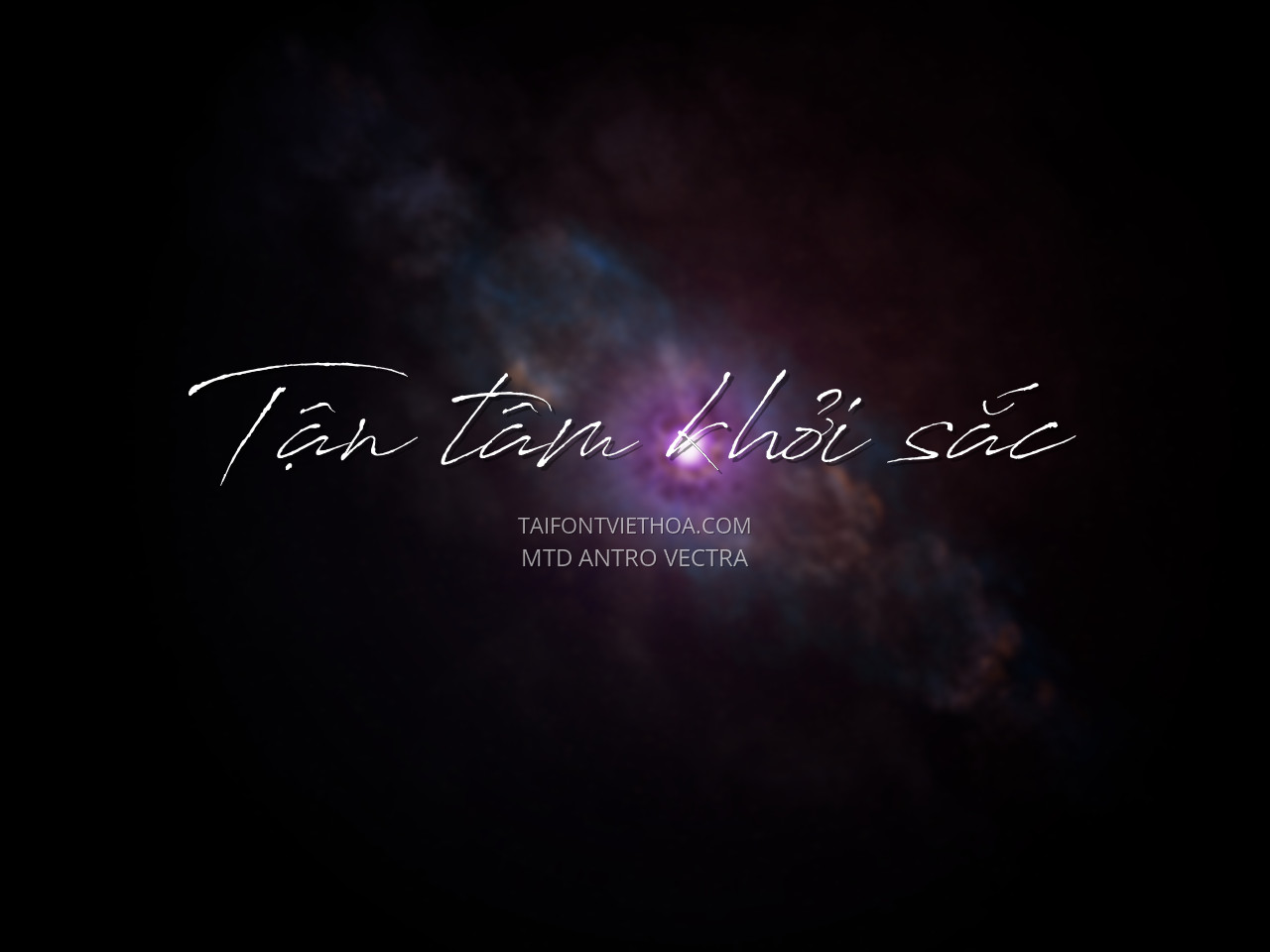
Giới thiệu về font Antro Vectra – Kiểu chữ chữ ký cao cấp, mềm mại và cá tính
Antro Vectra là một font chữ ký (signature font) hiện đại, nổi bật với đường nét mảnh, bay bổng và tự nhiên như nét bút viết tay bằng bút mực cao cấp. Font mang đậm tính cá nhân hóa, phù hợp với các thiết kế thương hiệu riêng, logo cá nhân, sản phẩm thủ công và các dự án cần thể hiện phong cách tinh tế, sáng tạo. Thiết kế gốc của Antro Vectra hướng đến sự thanh lịch và thời thượng – thường thấy trong các thương hiệu thời trang, mỹ phẩm, hoặc các blog phong cách sống.
Phiên bản Việt hóa do Mộc Hạthực hiện đã được chỉnh sửa và bổ sung dấu tiếng Việt đầy đủ, đồng thời vẫn giữ nguyên độ mềm mại và cá tính đặc trưng. Taifontviethoa.comđã chọn lọc và giới thiệu Antro Vectra như một font chữ ký lý tưởng dành cho các nhà thiết kế Việt, đặc biệt trong các dự án branding cá nhân, wedding design hoặc bao bì mỹ phẩm nữ tính.
Đặc điểm thiết kế chữ ký thanh thoát và ứng dụng của font Antro Vectra
Antro Vectra có form chữ nghiêng nhẹ, nét thanh mảnh, liên kết mượt giữa các ký tự. Điểm nổi bật là các ligatures và swash tạo ra những đường nét uốn lượn, mang đến hiệu ứng thị giác đẹp mắt. Đây là font chữ cực kỳ thích hợp cho những ai yêu thích sự thanh lịch nhưng không quá cầu kỳ.
Font lý tưởng để dùng trong: logo cá nhân, chữ ký thương hiệu, bao bì mỹ phẩm, nhãn handmade, thiệp cưới, trích dẫn nghệ thuật. Ngành nghề phù hợp gồm: mỹ phẩm, thời trang, wedding planner, lifestyle blogger, thương hiệu handmade và các sản phẩm cao cấp mang tính cá nhân hóa.